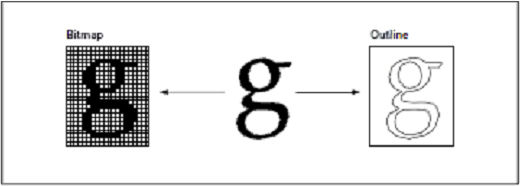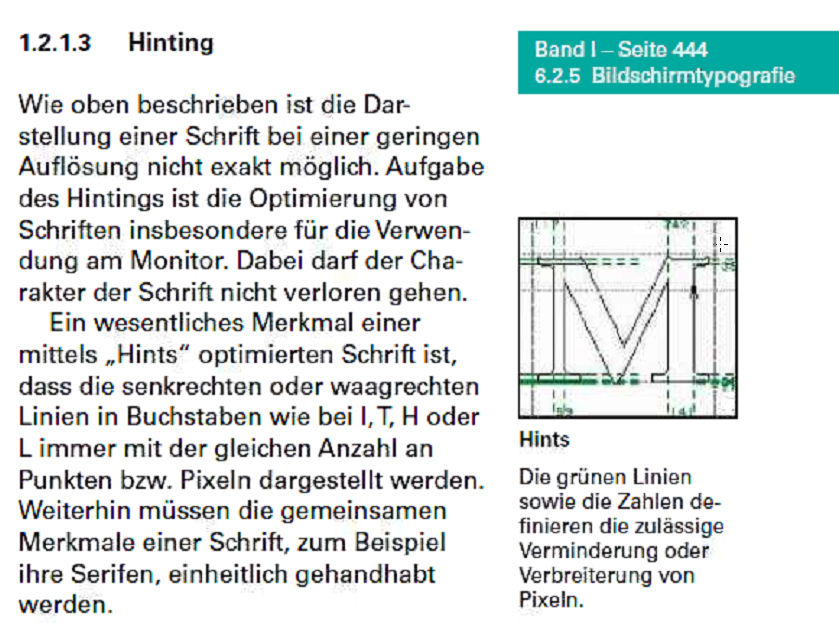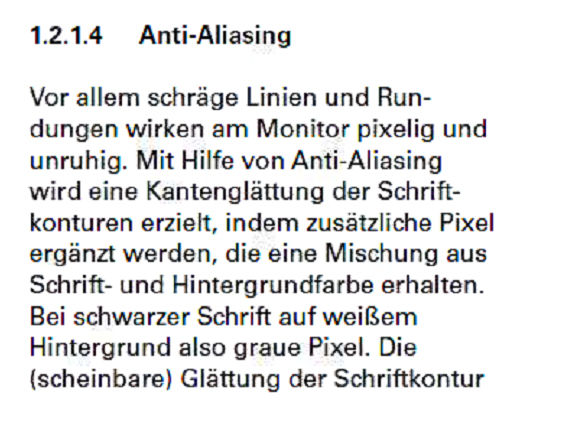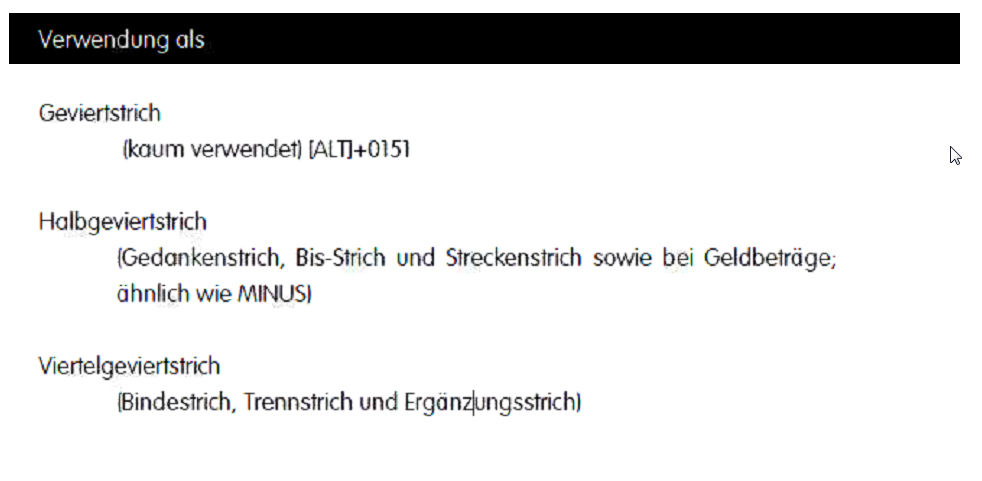
Datenhandling FONTS - Arten und Fachbegriffe
2. Schriftarten
1. BITMAP-FONTS / Pixelschriften
1. nur sehr eingeschränkt vergrößert und verkleinert werden
1. Rastergrafiken immer Details verlorengehe
1. Hoher Speicherbedarf
1. Abbild einer Schrift, die zur Darstellung auf dem Bildschirm genutzt wird
1. jeder Buchstabe in Form einer Matrix verarbeitet. Für jeden Buchstaben steht ein Raster zur Verfügung, in dem das Zeichen punktweise bezeichnet
1. Buchstaben werden zu einem Zeichensatz zusammengefasst und liegen dann in einer festen Größe mit fester Auflösung vor. Soll eine 72 dpi-Schrift auf einem 1200-dpi-Laserdrucker ausgegeben werden, wird sie dennoch nur mit 72 dpi gedruckt
1. verschiedene Schriftgrößen in akzeptabler Qualität darstellen, dann ist dies nur möglich, wenn es für diese Schriftart mehrere Zeichensätze für die unterschiedlichen Schriftgrößen
1. Bitmap-Fonts werden heutzutage in der Realität auf Computern so gut wie gar nicht mehr eingesetz
1. Als einziger Noch-Anwendungsbereich kommen Handys, PDAs und Pager in Frage. Auf diesen Systemen wird eine Schrift oft nur in einer einzigen Größe benötigt.
1. Kassenbons, Behörden-Ausdrucken auf Matrix-Druckern sind Bitmap-Schriften
2. Begriffe - Schnitte einer Schriftart
1. Strichstärke
1. Die Strichstärke ist ein Begriff aus der Typografie, der sich auf die Stärke der Linien, aus denen die einzelnen Buchstaben einer Schriftart bestehen, bezieht. Man unterscheidet dabei zwischen Schriftarten, bei denen die Strichstärke der Linien konstant ist (bzw. konstant erscheint), etwa bei Grotesk- und Egyptienneschriften, sowie Schriftarten mit variabler Strichstärke.
1. LEK TIP: Wissen was ist denn eine Condensed Schriftart? Was ist Bold etc.. ?
2. Ein Schriftschnitt (auch Schriftstil) ist eine Variation einer Schriftart. Hierbei werden unter anderem die Stärke, Laufweite und Lage der Schrift verändert. Mehrere verwandte Variationen werden als Schriftfamilie bezeichnet.
1. Ultraschmal (Ultra Condensed) Extraschmal (Extra Condensed; Thin) Schmal (Condensed; Compressed, Narrow) Halbschmal (Semi Condensed) Normal (Regular) Halbbreit (Semi Expanded) Breit (Expanded; Extended) Extrabreit (Extra Expanded) Ultrabreit (Ultra Expanded)
2. OUTLINE-FONTS / Vektorschriften
1. HIntings - KOmmentare - Hinweise
1. Immer lesbar; charakteristik erhalten, helfen Vektoren richtig zu Rastern, was muss erhalten bleiben, was darf nicht weg, ab 600 dpi nichtmehr erforderlich
1. Antialiasing - Der Aliasing Effekt
1. Darstellung der Vektoren auf Monitor benötigt Rasterung -> Treppenstufen (Aliasingeffekt) müssen dann durch Anti-Aliasing korrigiert werden
2. Was ist Kerning?
1. Kerningtabelle gibt Verhältniss einzelner Buchstaben unter und zueinander an
1. Fachbegriff aus der Typografie und bezeichnet dort den Vorgang, den horizontalen Abstand (den Weißraum) zwischen mehreren Buchstaben (Standarddickte) durch optischen Ausgleich so zu verringern, dass er gleichmäßig erscheint und so vom Betrachter als angenehmer empfunden wird
1. Was ist Geviert?
1. Das Geviert (englisch quad) ist eine typografische Maßeinheit aus der Zeit des Bleisatzes mit beweglichen Lettern, die auch im modernen Satz am Rechner noch verwendet wird
1. Das Geviert entspricht einer quadratischen (daher der Name „Geviert“, eine veraltete Form für Quadrat) nicht druckenden Fläche, deren Breite (Dickte) gleich der Höhe des Schriftkegels (der Kegelstärke) ist.
2. Höhe und Breite des Buchstabens bilden Wert für die Laufweite
1. Verwendung Geviert bei Geviertstrich; Halbgeviertstrich und Viertelgeviert:
1. EM stammt als relative Abstand von dieser Höhe/Breite/Laufweiteverhältnis
2. TIPP: OCR Texterkennung
1. macht aus Pixelbilder im Dokument wieder Vektoren (TEXT)
2. Welche Arten gibt es so? Type 1; Type 2? etc.. ?